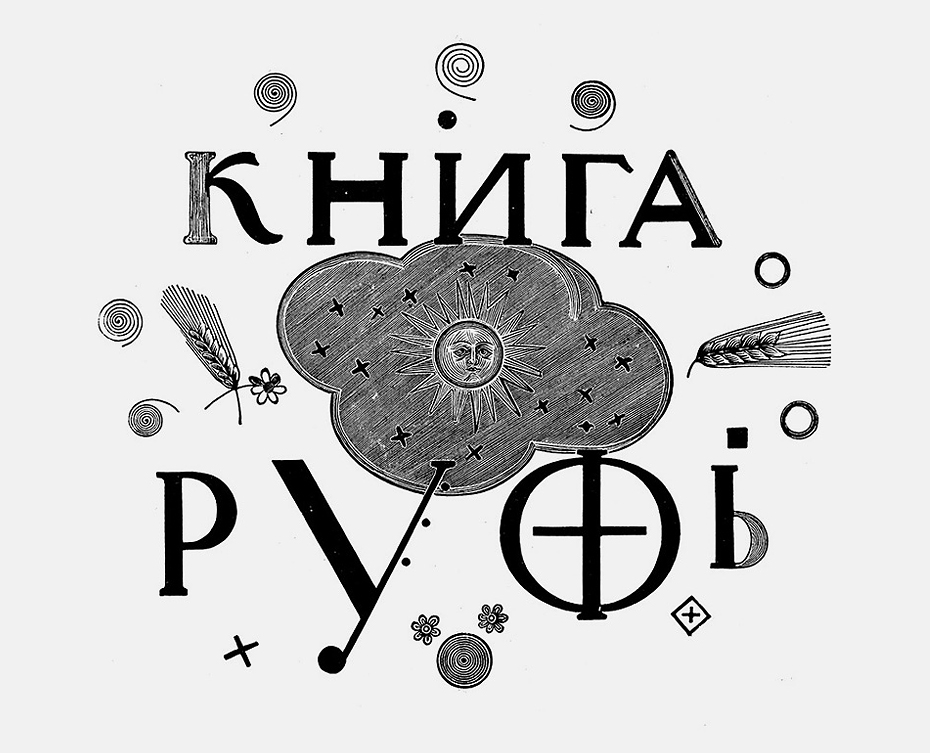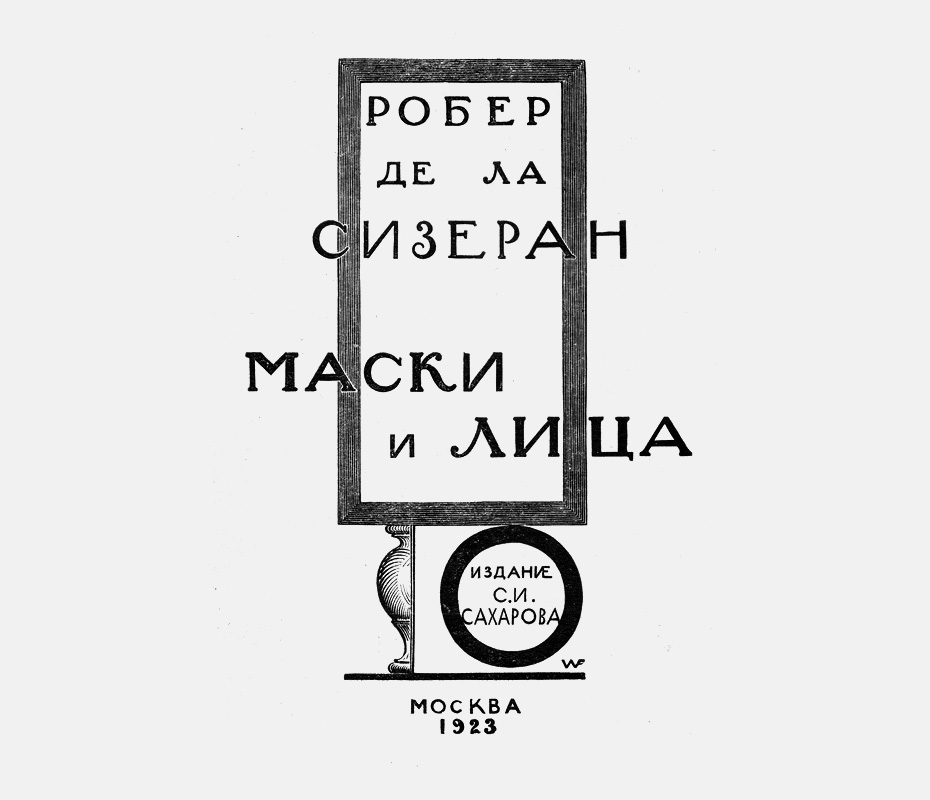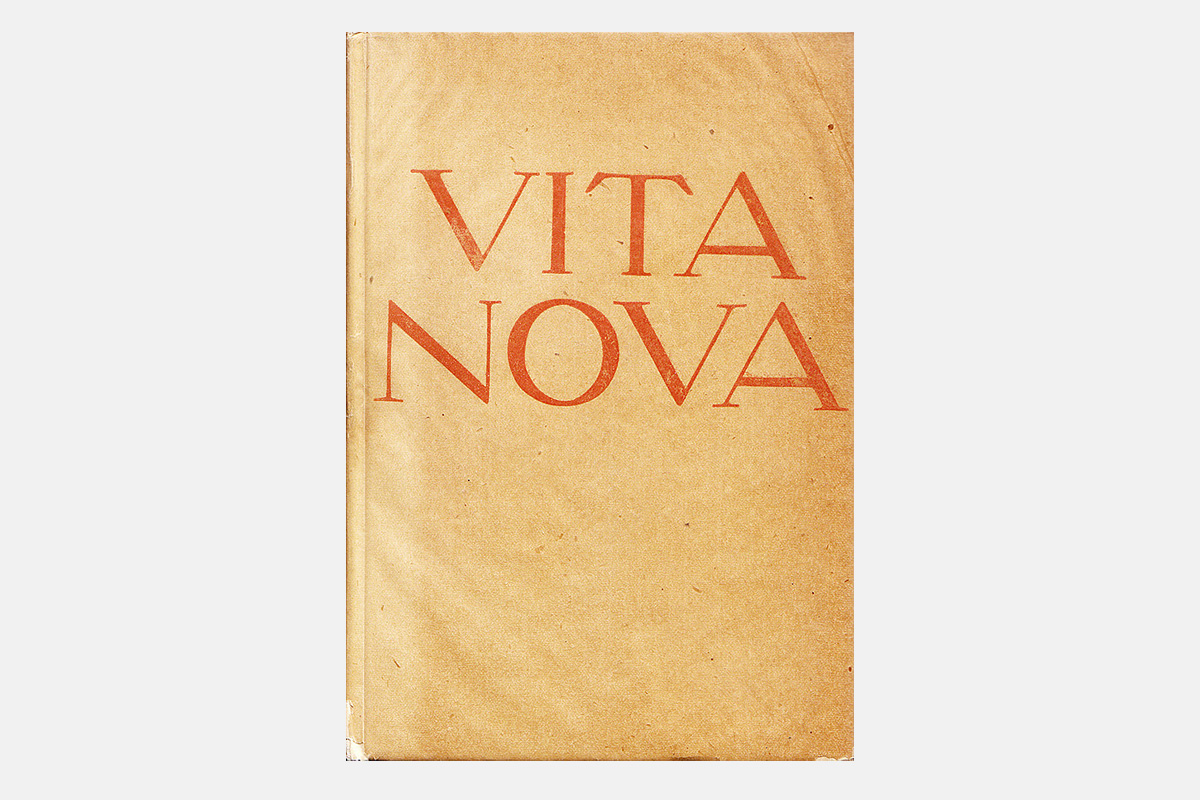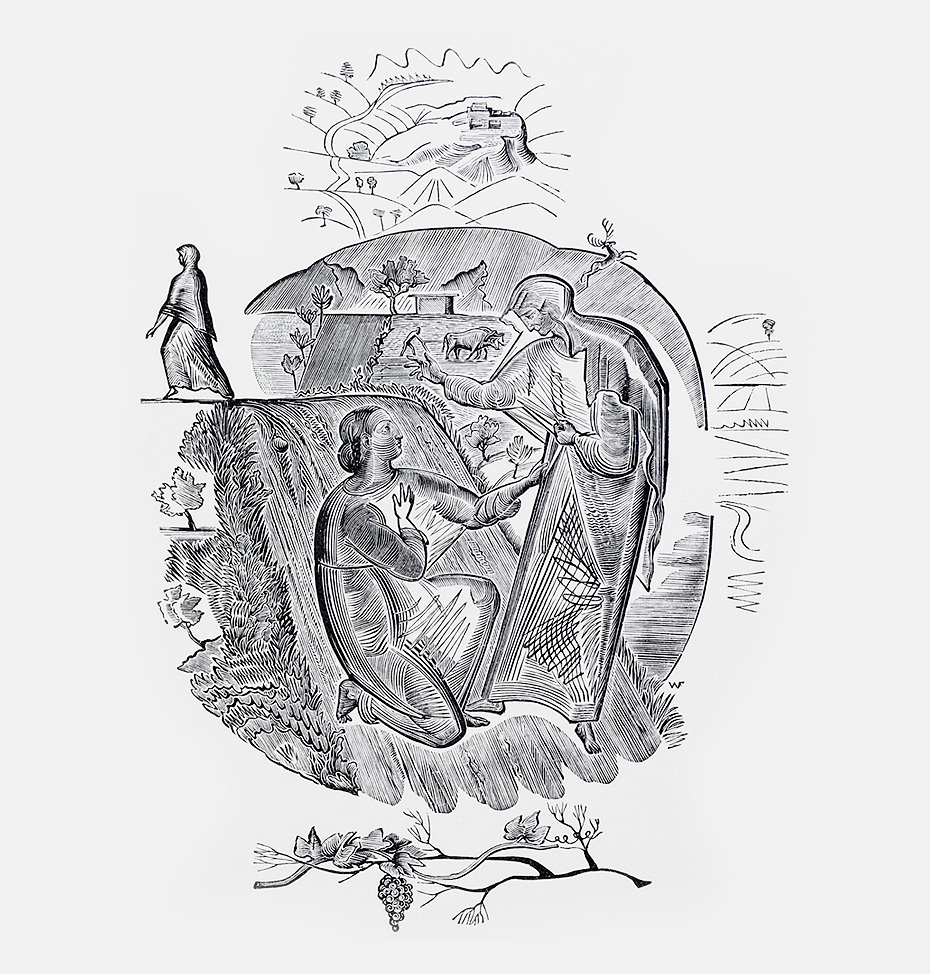
Юрий Герчук
о Владимире Фаворском
Cегодня мы публикуем фрагмент большого интервью (состоявшегося благодаря Мише Белецкому в январе 2011 года в Нью-Йорке) с Юрием Герчуком, где он рассказывает о Фаворском-теоретике и его учителях, о круге художников-современников и учениках. В своих работах Герчук не раз касался творчества Фаворского, его развития и влияния на искусство книги XX века. 1 марта 2014-го Юрия Яковлевича не стало, и мы вспоминаем этого человека, создавшего большой корпус книг и статей, близких не только профессиональному искусствоведу или художнику, но и графическому дизайнеру.
Юрий Герчук
Миша Белецкий
татьи и лекции об искусстве книги, монументальной живописи, театральном деле, архитектуре и даже оформлении городов — работа Фаворского-мыслителя касалась очень многих областей и велась на стыке различных искусств. Его наиболее значительные лекционные курсы носили краткие и конкретные названия: «Теория композиции», «Теория графики», «Теория книги». В них исследуются отношения предмета и изобразительного пространства, рассматриваются проблемы цельности художественного произведения, разрабатывается теория цвета и близкая шрифтовым дизайнерам тема взаимоотношений чёрного и белого пятна. Запланированный нами ряд публикаций о теории Фаворского продолжится главой «О шрифте» из статьи под названием «О графике как об основе книжного искусства» (1954, 1960). Редакция.
Творчество Фаворского и его подход к изображению кажутся мне ключевыми для понимания истории графики советского периода. В его подходе был некий мост, соединяющий традицию ВХУТЕМАСа 20-х и начала 30-х годов с ходом развития графики последующих лет. Большинство дизайнеров учились в Полиграфе, где преподавали ученики Фаворского, потом ученики учеников и так далее. Несколько поколений художников выросли на этой теории, которую им внушали без особых альтернатив — как единственный правильный путь.
Я думаю, что ваш подход несколько упрощён, книжное искусство в России развивалось сложнее. И линия Фаворского была только одной из линий, хотя и влиятельной в определённое время. Учили делать книгу не только в Полиграфе, многие графики учились в Суриковском институте, была ленинградская школа книжной графики, тоже существенно отличавшаяся от школы Фаворского.
П. Г. Беккер, С. Б. Телингатер и В. А. Фаворский. Москва, 1938.
Всё искусство, и книжное в частности, было политизировано. Теория Фаворского прошла сквозь все десятилетия, но прошла не гладко — было время, когда её усиленно отрицали.
В то же время появлялись новые тенденции, влияния. Даже когда Фаворский был преподавателем и ректором ВХУТЕМАСа, существовали альтернативные взгляды на книгу, например конструктивистская книга. Также в книжном искусстве того времени было много эклектичного. А с конца 30-х годов во главе официальной теории стоял чистый натурализм.
В. Гюго. «Труженики моря». Обложка. 1931. Ксилография.
Да, культура книги берёт начало в какой-то степени от Фаворского, но и в практике он многому научил своих учеников — художников конца 50-х и начала 60-х годов: живописцев, монументалистов. В эти годы они ходили к нему домой — как к классику искусства, не только книжного, причём в их числе были художники совсем не его направления, а более радикальные, будущие авангардисты. Дом Фаворского был одним из центров нового оттепельного искусства, того, что выставлялось на молодёжных московских выставках — оттуда шли новые веяния. В его доме жили ещё несколько художников — друзья, родственники, например, дочь Фаворского Мария Владимировна — художница-керамистка, зять — скульптор Шаховской. Одно время также живописец Дмитрий Жилинский и его жена Нина, скульптор.
Теория Фаворского мне представляется мистическим тайным учением, в которое «посвящали» учеников. И у «посвящённых» было иное внутреннее видение, чем у «непосвящённых» — хотя отчасти это учение было непрактичным и неприменимым на практике.
Вот с этим взглядом я согласиться не могу. В его теории не было ни тайны, ни мистики. И к практике она была применима, в значительной мере была теоретическим обобщением собственной практики Фаворского. Фаворский был не мистиком, а напротив — рационалистом, умел чётко объяснить смысл сложных художественных явлений. Но возникшие в 30-е годы официальные художественные предпочтения и взгляды были ными («социалистический реализм») и грубо навязывались. У Фаворского было много учеников, и что-то из его принципов они сохраняли в работе. Некоторые внешние черты круга Фаворского существовали как тенденция в книге. В Полиграфе преподавал Гончаров, который был учеником Фаворского. В своей работе он далеко ушёл от учителя, но всё же сохранял связь с его подходом. Дмитрий Бисти был учеником Гончарова, скорее «внуком» Фаворского по графическим тенденциям.
Однако влияние теории Фаворского на книжное искусство было ограниченным. Книга развивалась (в мире, не только в России) не так, как хотелось бы ему. Для него книга была замкнутым организмом. Рекламные тенденции, которые появлялись в книге, Фаворский не любил, сопротивлялся им — рекламная обложка была для него неприемлема.
Художественная культура в стране была такой, что теорию Фаворского не могли в полной мере воспринять даже ученики учеников Фаворского. Они не были подготовлены к восприятию этих идей и принципов. Этот подход не совпадал с художественным мировоззрением, которое в них вкладывала художественная школа. В более свободные времена бывали попытки возродить этот подход, но насколько они распространились, я не знаю.
Н. Симонович-Ефимова. «Записки петрушечника». Обложка. 1925. Ксилография.
Не были ли теории Фаворского слишком абстрактными?
Его теории не были абстрактными, они чётко связаны с книжной практикой его времени и его круга. Он не мог работать как художник-практик, не осмыслив теоретически то, что он делает. По его книгам можно проследить те теоретические принципы, которыми он руководствовался, — он сам это показывал в своих лекциях и статьях. Его теория обращена к структуре книги, к книжному пространству — там это всё было применимо.
Я имею в виду не ксилографию, которая неотрывно связана с его теорией, а скорее то, что называется дизайном.
Он делал не только ксилографию. Я знаю, например, одну малоизвестную работу — он делал один номер журнала (потом был ещё один, но это менее интересно) «СССР на стройке» в 1935 году. Номера были тематические, этот номер был посвящён охотничьему хозяйству, меху — на обложке была фактура овчины. Журнал фотографический — интересно смотреть, как принципы Фаворского легли на монтаж фотографий. Там не было никаких гравюр и ни одного штриха, напоминающего руку Фаворского.
Дизайн в современном смысле — явление более позднего времени. Его источником современные историки считают скорее конструктивизм. Между тем теория Фаворского ориентирована на художественную целостность книги. Рождение принципа макетирования сложно построенной книги совершалось в круге Фаворского. Он пишет, что в книге Толстого «Рассказы о животных» выбрал нужный ему шрифт, который соответствовал его стилю гравюры.
Насколько можно сказать, что школа Фаворского и школа ВХУТЕМАСа — это одно и то же?
Фаворский для графического факультета ВХУТЕМАСа — фигура капитальная и первоначальная. В книжных вопросах он определял школу ВХУТЕМАСа, потому что был одно время его ректором, руководил графическим факультетом, составлял программы. Вместе с ним преподавали его ученики, например Гончаров. Он привлёк во ВХУТЕМАС Флоренского — тот читал лекции с подачи Фаворского. Так что дух ВХУТЕМАСа для Полиграфа, который вырос из его графического факультета, — это в значительной степени дух Фаворского. Долгое время после Фаворского он держался силами Гончарова. Сейчас от прежнего, по-моему, мало что осталось.
П. Флоренский. «Число как форма». Обложка. 1926. Ксилография.
Кроме Фаворского были и другие педагоги, которые находились с ним в сложных отношениях. Например, конструктивисты, которые к Фаворскому могли относиться пренебрежительно — сами они графикам не преподавали, для них это было время борьбы со станковизмом. И Лисицкий, и Родченко преподавали во ВХУТЕМАСе, один из них вёл деревоотделочный факультет, другой — металлический.
В начале 20-х годов в Москву переехали несколько петербуржцев: Купреянов, Митурич, Бруни. К Фаворскому они первоначально относились недоверчиво. Купреянов уважал Фаворского и внимательно следил за тем, что он делает, но у него был свой путь. Есть интервью, в котором он говорит о своем двойственном отношении к Фаворскому — уважительно, но в то же время от влияний Фаворского отгораживается.
Студенты ВХУТЕМАСа с В. А. Фаворским и Н. Н. Купреяновым. Из личного архива Д. В. Житенёва.
Москва, 1926.
Бруни был человек жёсткий, говорил прямо, что думает, например: «Владимир Андреевич, а вы рисовать не умеете!» А Фаворский по мягкости характера отвечал: «Ну да, это же эскиз для гравюры, в этом смысле это не рисунок», хотя Фаворский рисовал не хуже Бруни и Митурича, он был блестящий рисовальщик. А Митурич был для Фаворского немножко слишком натуралист в рисунке. Они все были интеллигентные люди, хорошо между собой ладили, но творческие противоречия бывали и внутри ВХУТЕМАСа, и вне его.
В. А. Фаворский. Портрет М. В. Фаворской и Е. В. Дервиз. 1945. Карандаш. ГРМ, Санкт-Петербург.
Конструктивисты отрицали художественное творчество — эстетику, искусство, стиль. «Борьба за конструкции вместо стилей», — писал Маяковский, их лагеря человек. Для Фаворского отрицание стиля было даже теоретически неприемлемо. Он понимал, что без стиля произведение искусства не обходится, как бы вы ни старались. Чем больше стараетесь — тем больше стиля получится. Цитирую высказывание литературного критика Лежнёва по статье Юрия Александровича Молока, большого знатока книжного искусства и XX века, и 20-х годов в частности, о конструктивистской обложке: «Обложка у Родченко так же изысканна, как обложки Бердслея». Вообще, это, конечно, было оскорбление...
Александр Родченко. Обложка журнала «ЛЕФ». № 1, 1923. Источник: Lothar Lang. Konstruktivismus und Buchkunst. Edition Leipzig, 1990.
Впрочем, у Фаворского было своё, и не банальное, понимание термина «стиль». Стилизацию, подражание старым орнаментам и тому подобное он отвергал. Стиль был структурой представляемого произведением мира, «отношением предмета к пространству», «конечного к бесконечному».
Теория Фаворского, на мой взгляд, — это типичная теория художника, в её основе лежало его творчество, которое он осмыслял. Ему нужно было осмыслить теоретически то, что он делает, и вывести в слово. Но не столько слово служило основой того, что он делал на бумаге, сколько его интуитивное творчество осмыслялось и перерастало в теорию, поэтому в теории этой есть своя узость. Те творческие признаки, которые Фаворскому были не близки, его теорией отрицаются, хотя он не был человеком, склонным к противостоянию. Наоборот, он был склонен обдумывать всё, что ему предлагалось, даже явно враждебное, и если есть рациональное зерно его извлекать. Например, он считал, что лицо героя на переплёте невозможно. Оно должно быть внутри книги, потому что он противопоставлял внешность — внутреннему. «Книжка-кирпич в нашем пространстве и целый внутренний мир. Откроете — в мир этот нужно войти». Сейчас книга вся наружу открывается, и в его время так было, но он это критиковал.
Насколько его теория была оригинальной? Встречается мнение, что многое он почерпнул у Шимона Холлоши.
Я не уверен, что Холлоши был большим теоретиком, но что-то в принципах изобразительности Фаворский, конечно, у учителя взял. Холлоши не учил делать книгу, он был живописец. Идея изобразительной цельности всего, что делается, в том числе и в книге, идёт от немецкой школы, от Холлоши (хотя он был венгром) и от мюнхенских профессоров, чьи лекции Фаворский слушал в университете, когда учился в Мюнхене — там были хорошие искусствоведы.
Венгерский художник Шимон Холлоши (1857–1918).
Он многое взял у Гильдебранда, чью книгу перевёл вместе с одним своим соучеником, Розенфельдом. Гильденбранд — немецкий скульптор, классицист, который создал теорию изображения, изобразительной структуры, цельности изобразительной структуры. Это были основы, а Фаворский разрабатывал свою, достаточно тонкую систему, которая шла дальше теории Гильдебранда. Это имело прямое отношение не к книге, а к рисунку, графике, пластике, живописи (начинал-то он с живописи). Холлоши он очень уважал до конца жизни. Была идея собрать учеников Холлоши (он оказал большое влияние на многих русских художников, например на Истомина), организовать выставку, но в советское время этого сделать так и не удалось.
Расскажите о ваших встречах с Фаворским.
Это было в 60-е годы, я работал в журнале «Декоративное искусство», Фаворского только что стало можно печатать. Советская власть с 30-х годов его «оттирала», считала формалистом: статьи не печатались, книжные работы проходили с трудом. Он оформлял несколько книжек Маршака в поздние годы, видимо, Маршак сам этого хотел и сказал кому нужно — он мог себе такое позволить.
В. Шекспир. «Сонеты». Суперобложка. 1960. Ксилография.
И вот в «Декоративном искусстве» затеяли опубликовать Фаворского. Он прислал несколько статей. Но заместителю главного редактора, Карлу Кантору, некоторые философские ходы Фаворского не понравились — он решил, что надо править. Мне пришлось идти к Фаворскому, чтобы спросить разрешения, — очень было стыдно, должен сказать, до сих пор стыдно. Владимир Андреевич был тяжело болен, уже почти при смерти, ослабел, не вставал, говорил так, что я не понимал, — его шёпот «переводила» дочь. Владимир Андреевич лежал в постели, в маленькой комнатке, перед глазами его на стене висела маленькая прелестная картина Петрова-Водкина, к которому он относился с большим почтением. Я говорил ему про сомнения редактора, про то, что надо изменить. Он практически на все правки согласился, и мы напечатали искажённый текст. Уже потом в сборнике его статей эти тексты были напечатаны по рукописям правильно.
«Книга Руфь». Обложка. 1924. Ксилография.
Если посмотреть на книги Фаворского, изданные в 20-е годы, и сравнить их с поздними книгами, заметно, что его стиль изменился на более реалистичный.
Конечно, атмосфера влияла (не только внешнее давление) — но в тех пределах, которые не нарушали его принципов и убеждений, при всей его внутренней мягкости. Я не думаю, что «Борис Годунов» сделан иначе, чем «Книга Руфь». Пильняк — книжка, особняком стоящая, ничего похожего у Фаворского больше нет. Я думаю, что это скорее общее влияние художественной атмосферы, которая стала другой, и работать так, как в 20-е годы, стало нельзя. Внутренне нельзя, не только по внешним причинам.
Всегда были люди, которые считали, что настоящий Фаворский — ранний, были люди, которые считали, что настоящий Фаворский — поздний. Для меня Фаворский ранний интереснее, потому что он более чист стилистически. Тем не менее он не отрекался от поздних работ. Были художники, которые говорили: «Заставляли делать так, что лучше бы этого времени не было». Конашевич так говорил о второй половине 30-х годов. Тогда, например, рисуя иллюстрацию, нужно было изобразить и комнату, в которой всё происходит, — на чистую бумагу нельзя было положить рисунок. Конашевич так делал, но считал это неправильным и говорил об этом в поздние годы. А у Фаворского таких высказываний нет.
Он себя никогда не считал авангардистом?
Нет, слово это несколько более позднее, но его интересовали авангардное искусство, поэзия. Хлебникова любил, например.
При этом он не был традиционалистом тоже?
Традиционалистом он тоже не был, у него был свой путь. Он считал, что у искусства есть законы, которые нарушать нельзя, — произвола быть не должно, всё должно быть обоснованно. А авангардисты часто ломали традицию любой ценой и делали вещи, которые Фаворский считал бы необоснованным отказом от законов искусства.
Кем он себя представлял?
Я за него сказать не могу. Естественно, Фаворский считал себя художником, но он был и профессиональным искусствоведом. После мюнхенской школы он окончил московский университет, отделение, недавно тогда основанное, «археологии и искусствознания». Есть его статья, даже глава из детской книги «Рассказы художника-гравёра» (М.: Детская литература, 1976). Там в первой главе «Что меня характеризует как художника» он пишет, кем он себя считал. Почитайте.
Литература
1. Книга о Владимире Фаворском / Сост. Ю. А. Молок. — М.: Искусство, 1967.
2. Фаворский В. А. Рассказы художника-гравёра. — М.: Детская литература, 1976.
3. Фаворский В. А. Об искусстве, о книге, о гравюре. — М.: Книга, 1986.
4. Фаворский В. А. Литературно-теоретическое наследие. — М.: Советский художник, 1988.
5. Герчук Ю. Я. «Книга Руфь» — шедевр В. А. Фаворского // Сб. 80. — М.: Наука, 2002. —
С. 272–299.
6. Герчук Ю. Я. Форзацы В. А. Фаворского // Сб. 79. — М.: Терра, 2001. — С. 120–138.
На са­мом де­ле В.Ф. де­лал ещё два но­ме­ра жур­на­ла: № 3 1936 го­да и № 2 1937 го­да. — Прим. ред.